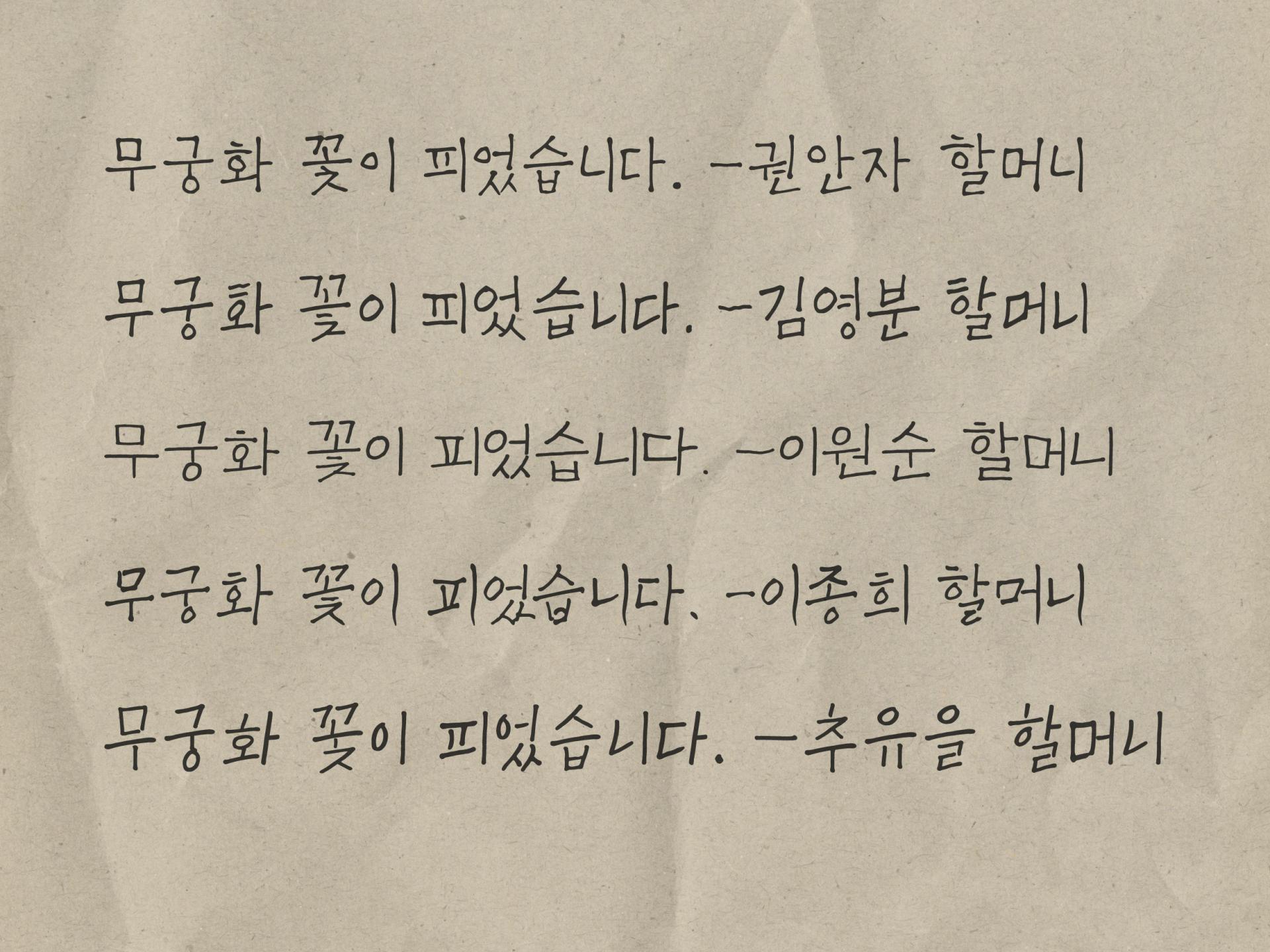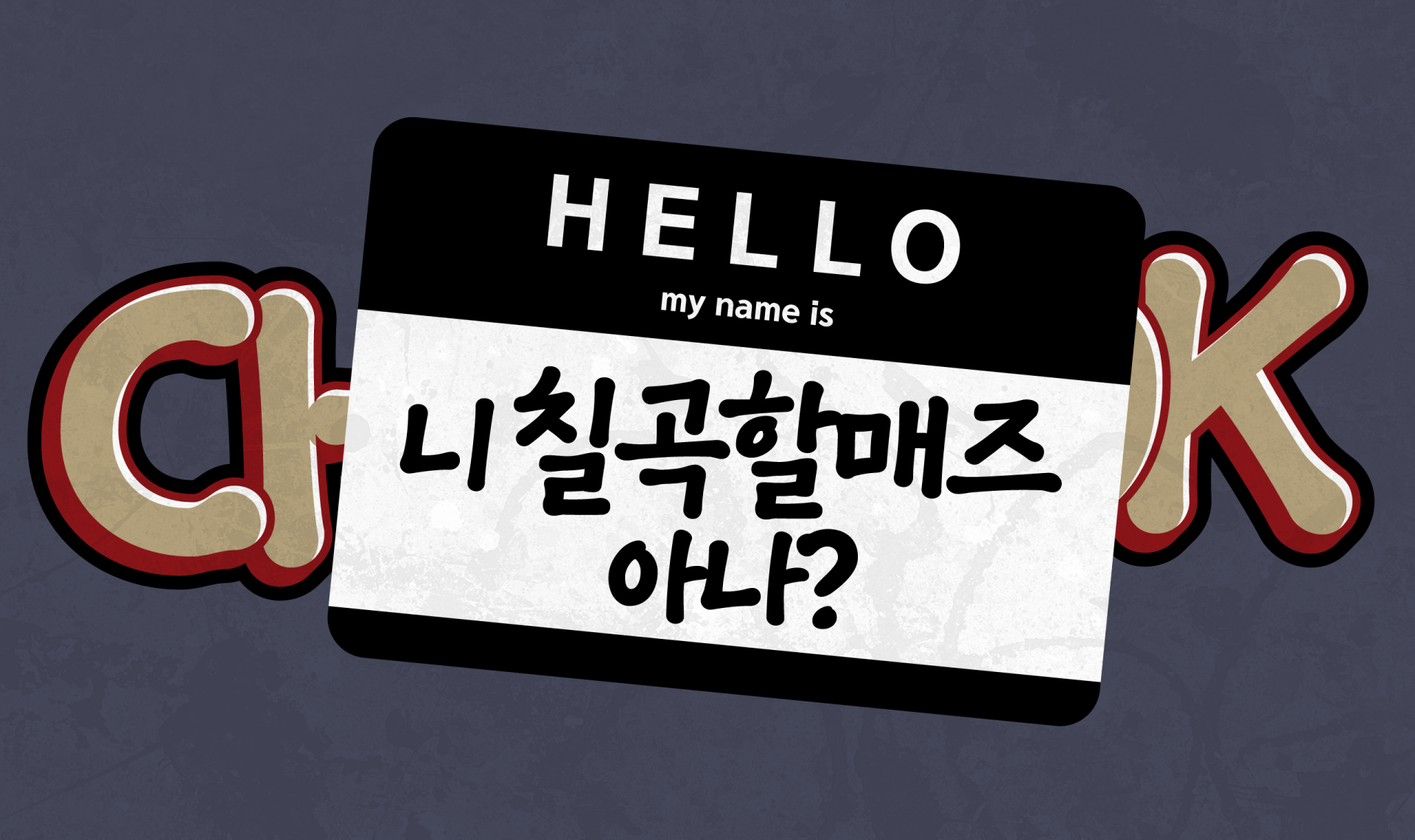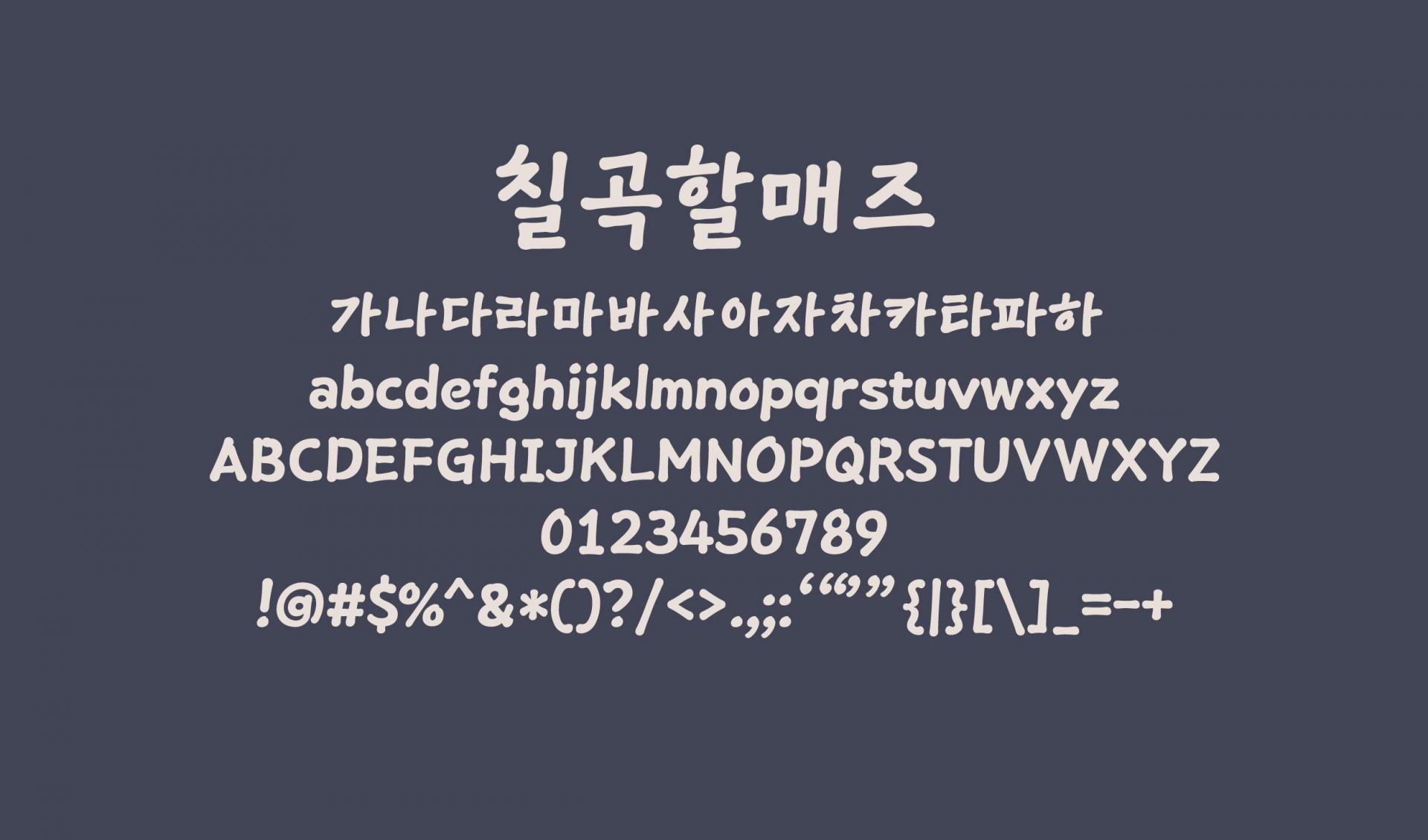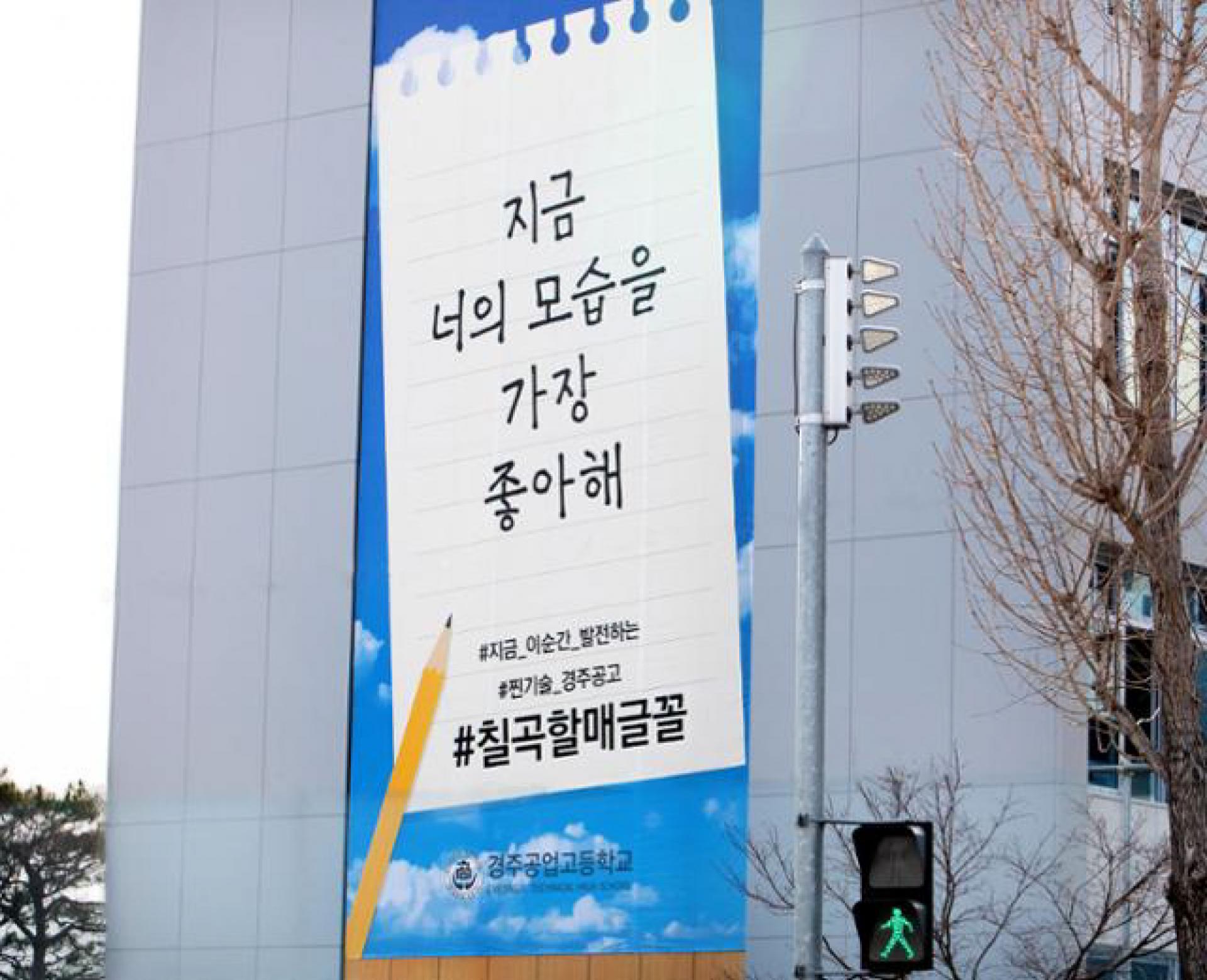
경상북도 칠곡군의 [칠곡할매체]는 해당 군의 '성인문해교육'을 통해 한글을 배우는 어르신 5명의 이야기를 담아 약 4개월간 한명당 2천장의 종이에 연습한 끝에 탄생한 폰트이다. 한글을 깨우치고 마음 속 담아둔 이야기를 글로써 가족들에게 전할 수 있게 된 5명의 할머니들에 대한 이야기를 담았다. [칠곡할매즈]는 칠곡할매체의 일부를 ExtraBold로 재해석하여 트렌디함을 더한 폰트이다.